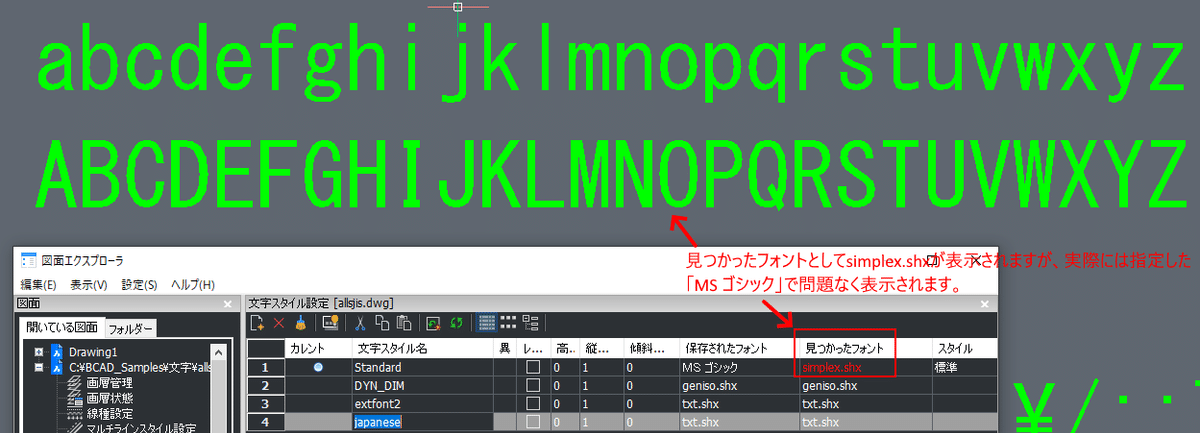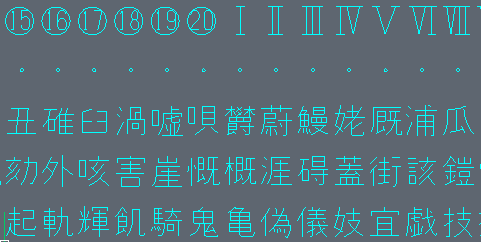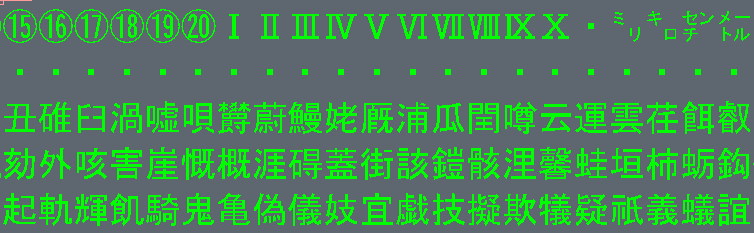
BricsCAD で使えるフォントファイル
まずはじめに、BricsCADでは図面作成に次のフォントファイルを利用することが出来ます。
TreuType (.ttf / .ttc)フォントについて
いわゆる OS で標準的に使われるフォントファイルの一つです。"MS ゴシック"、"MS 明朝" などCADを使わない方にも馴染みのあるファイルです。
BricsCAD上でのTrueTypeフォントの表示
TrueType フォントは、OS にインストールされているフォントがそのまま利用できます。
TrueType フォントでは注意が必要な点があります。TrueType フォントにはいくつか種類あるのですが、BricsCAD で利用できるのは、TrueType アウトラインのフォント で、その他の OpenType アウトラインや、PostScript アウトラインタイプのフォントは利用できず文字スタイルのフォントリストなどにも表示されません。(これは他の主要な .dwgベースCADも同様です。)
Windows の日本語版に標準搭載されている游ゴシックの例
OpenType アウトラインのフォントは、TrueTypeアウトラインのフォントよりも新しく、TrueTypeの上位互換的な形でより高機能なフォーマットと言えるので対応していてもおかしくないのですが、.dwgファイルが標準的なフォーマットとして使用されるほとんどのCADでは、データ互換の観点からか同様の仕様になっています。
SHXフォント(.shx)フォントについて
SHXフォントは、AutoCAD®用として使用され始めたストロークフォントです。TrueTypeが文字のアウトラインを定義したものであるのに対して、文字の骨格を線で表現するようなフォーマットになっています。
SHXフォントの表示
BricsCAD V23 では、次のSHX フォントが標準搭載されています。
V23 に含まれている SHXフォントと内容
SHXフォント(.shx)フォントの(マルチバイト圏向け)ビックフォントについて
SHXフォントは、英語圏から始まり日本語や中国語、韓国語などシングルバイト(ASCII範囲)で表せない文字への対応を付け足しするような形で行われたという経緯から、マルチバイト圏向けの SHXフォントとして "ビックフォント" を指定するという形態が一般的に利用されています。
上の表にある薄いオレンジ背景色のファイルが BricsCAD に標準搭載されているビックフォント用のSHXフォントです。
SHXフォントもその後ユニコードタイプの仕様が出来たので、実はビックフォントを使わずに多国語表示することも仕様上は可能になっています。
ただ、中の人が把握している範囲では日本・中国・韓国語などマルチバイト圏の文字を包括的に含んだようなSHXフォントは存在していません。
中の人の私見としては、多言語表示ではTrueTypeフォントを使用するほうが汎用性が高く、また コンピュータや CAD の性能がかなり向上しているため SHXフォントを作るメリットがあまりないためといえるかもしれません。
BricsCAD の日本語SHXフォント環境
BricsCAD でも、日本語のSHXフォントは標準搭載されていますので、特に設定をすることなく日本語を利用可能です。
標準搭載されている日本語のSHXフォントは次のとおりです。
- Extfont2.shx
- Japanese.shx
2つのフォントは字形のデザインは同じでJIS第2水準相当の文字を含んでいるフォントファイルです。違いは、Extfont2.shx が他の CAD にある同名の SHXフォントファイルに対してデータ再現性を高めるため、文字の位置や幅を崩さず再現されるように調整されているという点です。
他CADからのSHXフォント流用
代替(置換)フォントの仕組み
図面ファイルで使用されているフォントがなかった場合、図面を開くとメッセージが表示されたりします。ここで、「フォント置換を指定」をクリックすると、見つからないフォントに対して、別のフォントで表示する設定ができます。
欠落フォントがある図面を開いた際のバルーンメッセージ
フォント置換の設定ダイアログ
それぞれのフォントに対して使用するフォントを選択して設定できます。
また、フォントマッピングファイル(以降、フォントマップファイル)によって、あらかじめ別のフォントを使用するようにセットしておく仕組みがあります。これにより文字が表示されなくなる事態を避け、異なる環境からのデータ表示をコントロールすることが出来ます。
なお、TrueType フォントについては OS のフォント置換の仕組みによっても置換表示されます。設定はフォントマップファイルの設定が優先的に適用されます。
フォントマップファイルの設定
フォントマップファイルは、フォントが見つからなかったときに、変わりにどのフォントを使用して表示するかを設定する設定ファイルです。
BrcsCAD では default.fmp というファイルが既定のフォントマップファイルとして設定されています。
フォントマップファイルはテキストファイルで、中身の記述は1行毎に次のようにセミコロンで区切った記述になっています。
置換前のフォントファイル名;置換後のフォント名
ファイルを開くと下のイメージのようになっています。
default.fmp をメモ帳で開いた例
赤枠部分は日本語のビックフォントの置換設定の記述です。
他のCAD でアドオンアプリケーションを利用していて BricsCAD に移行する際は、場合によってはフォントマップファイルに追加・変更することでスムーズに移行する事ができます。
例えば、 bigfont.shx を extfont2.shx に割り当てたい場合、次のような記述になります。
bigfont.shx;extfont2.shx
フォントマップでも見つからなかった場合の文字表示
フォントマップで置換するフォントが見つからなかった場合、最終的には、BricsCAD の 代替フォント に設定されたフォントで表示することが試みられます。
代替フォントの設定は、オプション設定から行いますが、初期値はsimplex.shx フォントが指定されています。代替フォントにビックフォントも含めたい場合は、下記のように shxフォント名,ビックフォント名 を設定します。
代替ビックフォントのとして extfont2.shx を設定した例
TrueType フォントに代替表示するようにしたい場合は、TrueTypeフォント名を指定します。
なお、ビックフォントの代替指定は Truetypeフォントの代替としては効きませんのでご注意下さい。
以上のように、BricsCAD では文字化けしないようにするための仕組みが整っています。正常に表示されていない場合は、設定上の問題であることがほとんどですので、安心してご利用ください。
CAD インターフェスのフォント表示設定
BricsCAD のUI上のフォントを変更可能な部分もあります。
ひとつは、コマンドラインのフォントです。コマンドラインのフォントは、オプション設定の「コマンドラインフォント名」で変更します。「フォントサイズ」でサイズも変更できますので、小さすぎて読めない!という人は大きな数値に変更してみて下さい。
設定ダイアログ
左は標準の Consolas、右は「游ゴシック」に変更した状態
もう一つは、BricsCAD の LISP 開発環境である BLADE のフォントです。
設定方法は次のとおりです。
1.BLADE コマンドを実行します。
2.メニューから[設定]-[設定ダイアログを表示]を選択します。
3.スタイルタブをクリックします。
4.エディタ色とレクサースタイルそれぞれを設定をします。
エディタ色では、BLADE IDE の表示設定、レクサースタイルでは、編集するファイルの種類ごとの表示を設定することが出来ます。
設定は、各行の項目を選択して下部にあるフォントを有効にして変更します。まとめて設定したい場合は、SHIFTキーを押しながら、複数項目を選択後にフォント選択します。
5.設置が終わったら適用ボタンとOKボタンをクリックして終了します。
BLADE の設定画面
日本語フォントに関連した既知の問題(~V23)
*この問題は BricsCAD V24 で改善されています。
BricsCAD V23 日本語版の未解決な既知の問題として、文字スタイルで一部のTrueType フォントを設定しているときに 「見つかったフォント」の項目に TrueType フォントのファイル名ではなく fontalt のフォントが表示されるケースがあるという問題 があります。
例. 見つかったフォントに表示されている simplex.shxではなく、指定されているMSゴシックで表示されています。
少々気持ちの悪い状態ですが、実際には指定したフォントが表示されるので設定表示上の問題です。
以上、BricsCAD®の日本語フォント対応ということで、BricsCAD のフォント周りについて解説いたしました。
AutoCAD からの移行を検討される方は、同様な仕組みで環境が整えられるとお考え頂いて差し支えありません。